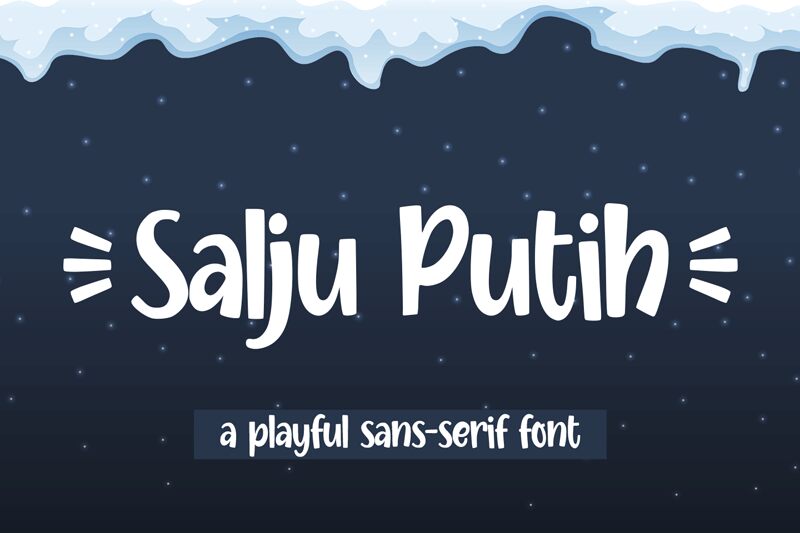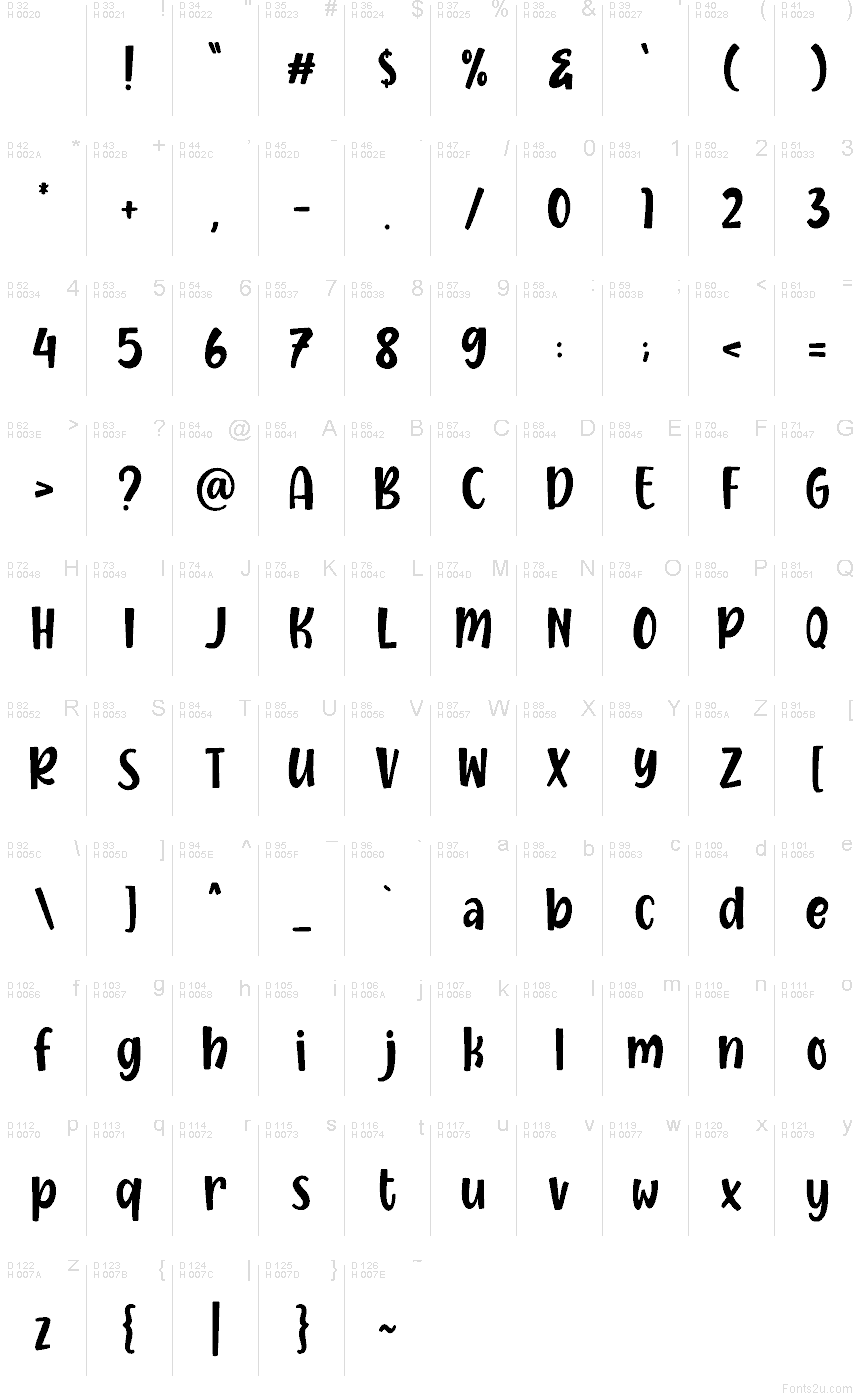
Salju Putih od Abo Daniel Studio to darmowy krój pisma typu comic display o luźnym, odręcznym charakterze. Litery są wysokie, miękkie i lekko nieregularne. Zaokrąglone kreski i żartobliwe krzywizny nadają słowom niezobowiązujący, naturalny rytm, daleki od sztucznej gładkości kreskówkowych fontów.
Idealnie sprawdzi się w brandingu dla młodych, na opakowaniach przekąsek, w wesołych nagłówkach plakatów, na okładkach książek oraz w grafikach do mediów społecznościowych, wszędzie tam, gdzie zależy Ci na przyjaznym, ale nie przesłodzonym stylu. Jako darmowy font, świetnie nadaje się też do krótkich logotypów, menu w kawiarniach czy wyeksponowanych cytatów, ponieważ nierówny ruch liter sprawia, że nawet kilka słów wygląda żywo.